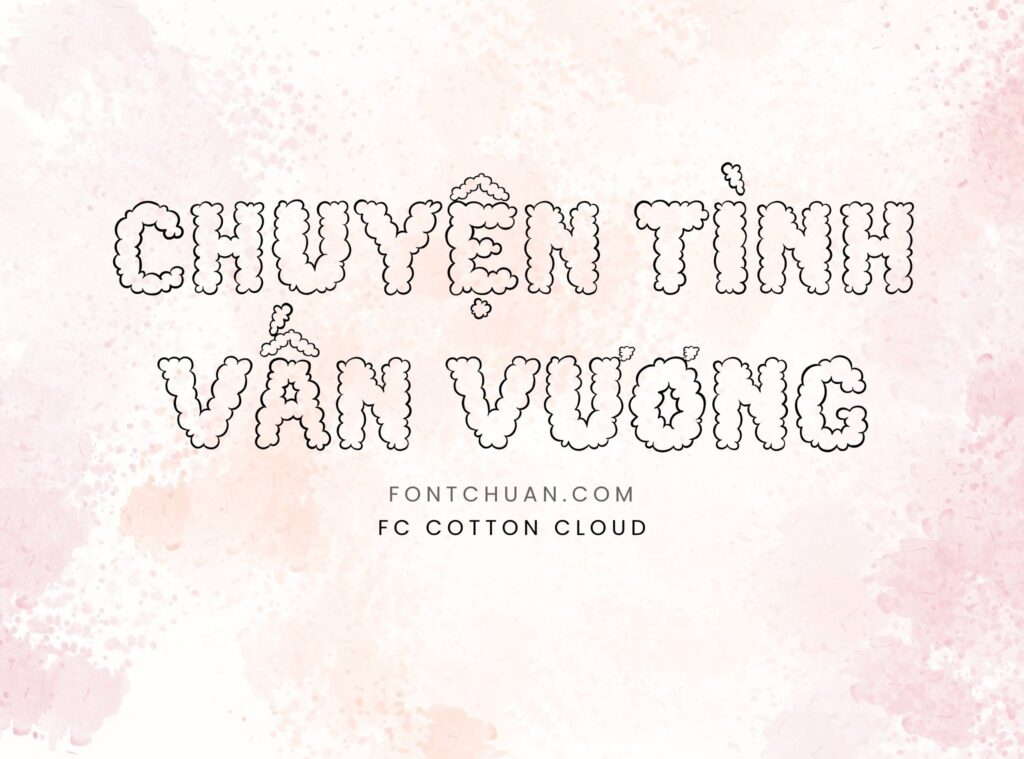
Font FC Cotton Cloud Việt Hóa (hoàn thiện nhất)
Tác giả Font: Tokokoo
Việt hóa bởi: Font Chuẩn
Cotton Cloud là một font chữ trang trí độc đáo, được thiết kế bởi Tokokoo Studio và phát hành vào khoảng năm 2021. Với thiết kế mềm mại và bồng bềnh như những đám mây, font này mang lại cảm giác nhẹ nhàng và vui tươi nhất, phù hợp như một Font Lễ hội để trang trí các sự kiện đặc biệt.
FC Cotton Cloud được việt hóa và chia sẻ miễn phí bởi Font Chuẩn, bản việt hóa này Font Chuẩn đã cố gắng hoàn thiện, bạn dễ dàng nhận ra chất lượng vượt trội so với các phiên bản khác đang có trên thị trường, hỗ trợ tốt cho tiếng Việt, tiếng Anh và hơn 12 ngôn ngữ Latin khác, mở rộng khả năng ứng dụng cho nhiều dự án quốc tế.
Với cấu trúc chữ mềm mại, độ dày đồng nhất và thiết kế tinh tế, FC Cotton Cloud phù hợp cho các thiết kế cần sự hồn nhiên, ấm cúng và thân thiện. Đặc biệt, font này thích hợp cho các ngành nghề như quảng cáo, thiết kế thiệp mời, thiệp cưới và lĩnh vực giải trí, nơi cần sự kết hợp giữa thẩm mỹ vui tươi và chức năng truyền tải thông điệp.